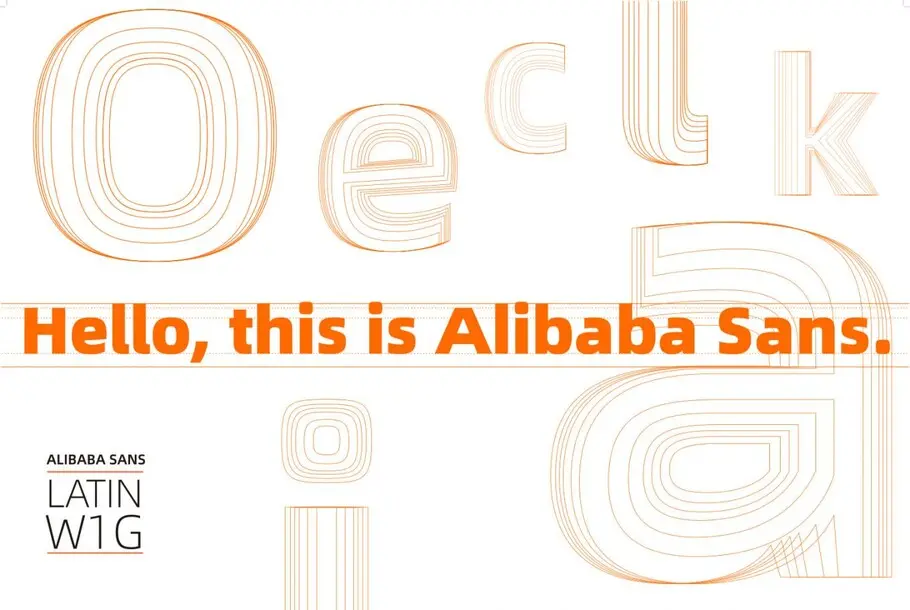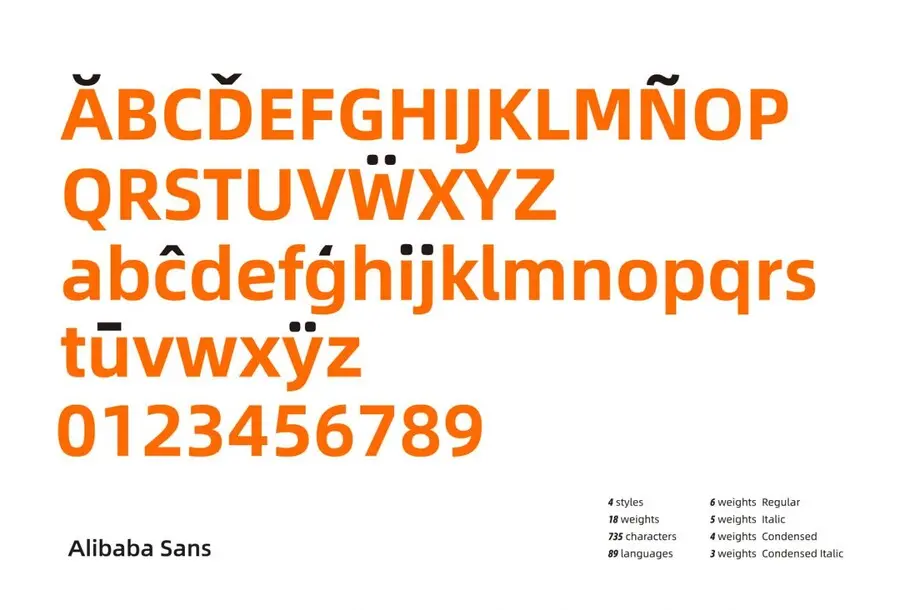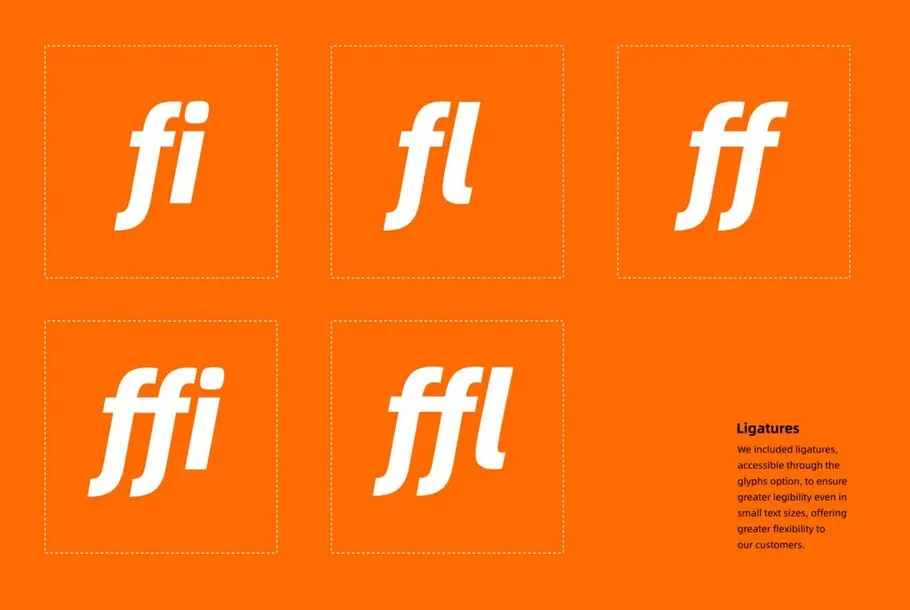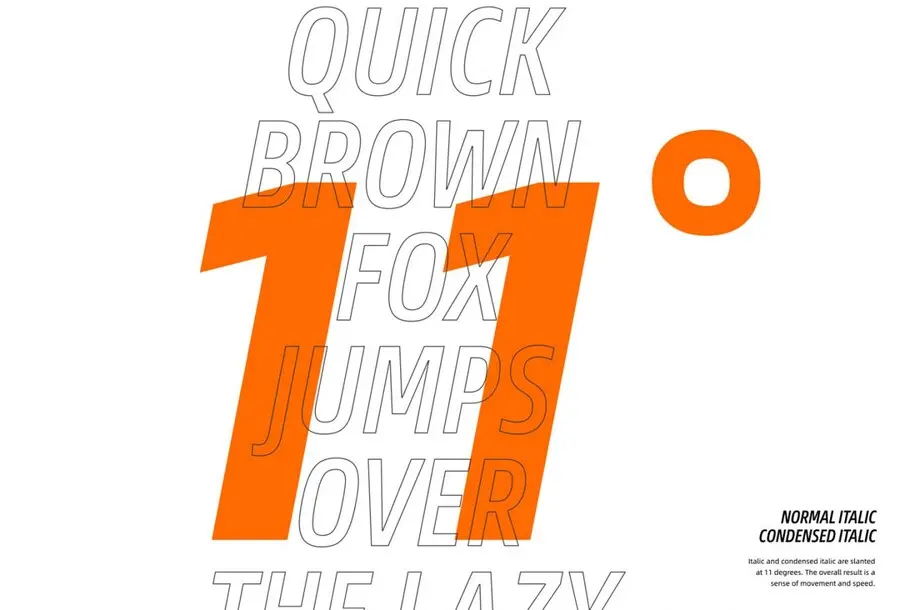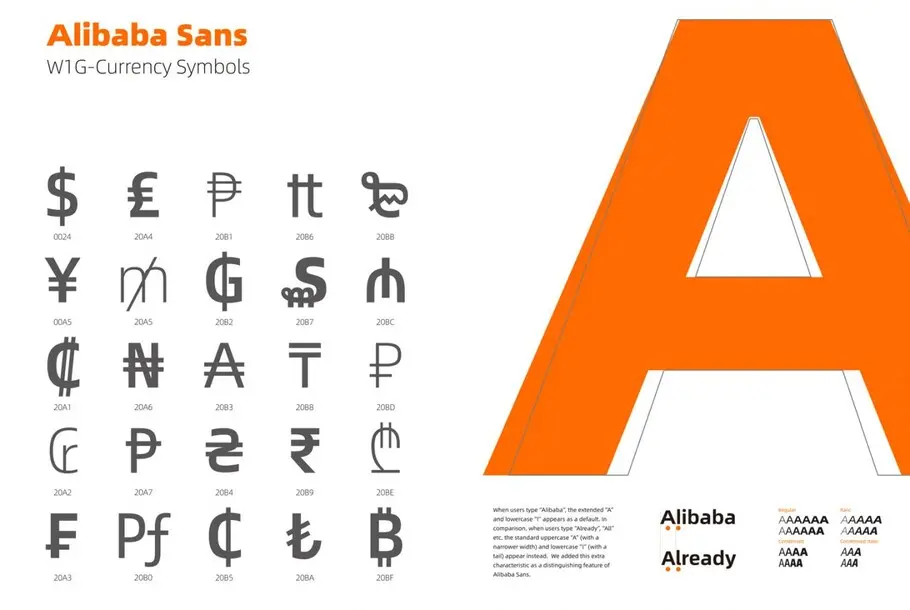
アリババグループの新書体が企業のエコシステムにシンプルな美的センスをもたらす
「 Monotype understood our unique challenges and delivered a typeface that will take us to the next level in our branding efforts. 」
Alibaba Sans
アリババグループのためにカスタムデザインされたフォントファミリー Alibaba Sans で、ブランドイメージにぴったりマッチしたデザインをグループ全体で共有することが可能になりました。
課題
アリババグループの企業ブランディングチームは、複数のクリエイティブチームやオフィス拠点、そして多様なデジタルパートナーやサプライヤーを含めたエコシステム全体にわたり、複数のオープンソース・フォントを使用していたため、デザイン上の様々な困難に直面していました。
同社の急成長により、デザイナーが自由に実験しつつも、ブランド及び IP 規範内に収まるような一貫性があり、柔軟かつ革新的なフォントファミリーの必要性を高めました。Eコマースおよび小売事業が中心のビジネスであることを考慮すると、Alibaba グループにとっては文字だけでなく、数字や通貨記号のフォントも最重要になる点が浮かび上がってきました。課題をさらに深めたのは、ブランドイメージにマッチするキャンペーンを企画制作するために、今も成長を続ける市場全体においてチームメンバー、パートナーそしてクライアントと手軽にアリババブランドのフォントを共有する必要がありました。
ソリューション
実に協力的な各チームメンバーの取り組みの下、Monotype と アリババグループのデザインチームは、数日間にわたるワークショップを複数回開催しました。ワークショップでは、アリババグループの企業アイデンティティを体現した新しい書体コンセプトを迅速に開発するためにデザイン活動に集中しました。
Monotype のタイプディレクター小林章(こばやし・あきら)率いるデザインチームは、アリババグループの Eコマース事業において非常に重要である数字および通貨記号をまずデザインすることで、 アリババの課題に応え始めました。数字や文字を一からデザインすることで、特徴ある小文字の「a」を含めた Alibaba Sans を制作しました。求められたフォントは、最大の太さでも目に優しく、大小どのサイズでも読みやすく、デバイスからオフィスビル標識、アリババギフトショップ、実店舗および全ての Eコマースサイトどこでも使用できるものでした。
アリババグループを具現化する最も印象に残る言葉を捉えるために、世界中の従業員アンケートが作成されました。その結果、デザイナーたちは Alibaba Sans フォントに「情熱的」「パワフル」そして「未来志向」のエッセンスを込めました。このカスタムフォントファミリーは、2019年4月27日~28日にかけて開催された Alibaba Design の UCAN フェスティバルで発表されました。デザインの力を通して「シンプルで美しく」あるための完全なシステムフォント一式がグループ全体にわたり共有できるようになりました。
「 「Monotypeは、Alibabaグループ特有の課題を理解し、ブランディングに関する取り組みを一段レベルアップさせてくれるフォントを届けました。真のエキスパートとして、そして当社チームの延長として、ご協力いただいたことに深く感謝しています。この新書体は、世界中全てのパートナーおよびクライアントに対して無料のリソースとして提供したいと考えています。グループの使命に忠実であるためにも、中小規模の起業家たちがデザインの力を通してデジタル経済に参加することを支援するための確たる一歩を踏み出しました。ーAlibabaグループ・チーフマーケティングオフィサー 菫本洪(クリス・トン) 」
成果
社内向け:
• 企業全体で、使いやすく統一され、一貫性のあるブランディングを届ける
• センスのあるキャンペーンを試し、最高品質かつ柔軟なIPを活用し企画制作する
• 協働、デザインのスピードおよび ROI を伸ばすために、書体を各事業部に迅速に展開する
• 全てのデザインタッチポイントで使いやすさを可能にする
外部向け:
• 統一性のあるブランドイメージおよび企業イメージを伝える
• クライアントやパートナーがカスタムフォントファミリーを全てのタッチポイントで識別し使用することで市場での混乱を一掃する
• 無料の新書体を届けることで、ブランドイメージにマッチしたデザインを促進する
「 「Alibaba グループの直面した課題は、オンラインとオフラインの多様な環境下でブランド価値を伝える必要があるという、一般的でありつつも、なかなか難しい問題でした。フォントの重要性に尽力するチームと協力できたこと、それと Alibaba グループがブランドを統一させる際にカスタムフォントが持つ可能性を認識する支援ができたことを光栄に思います。」ーMonotype 社クリエイティブ・タイプディレクター 小林章 」